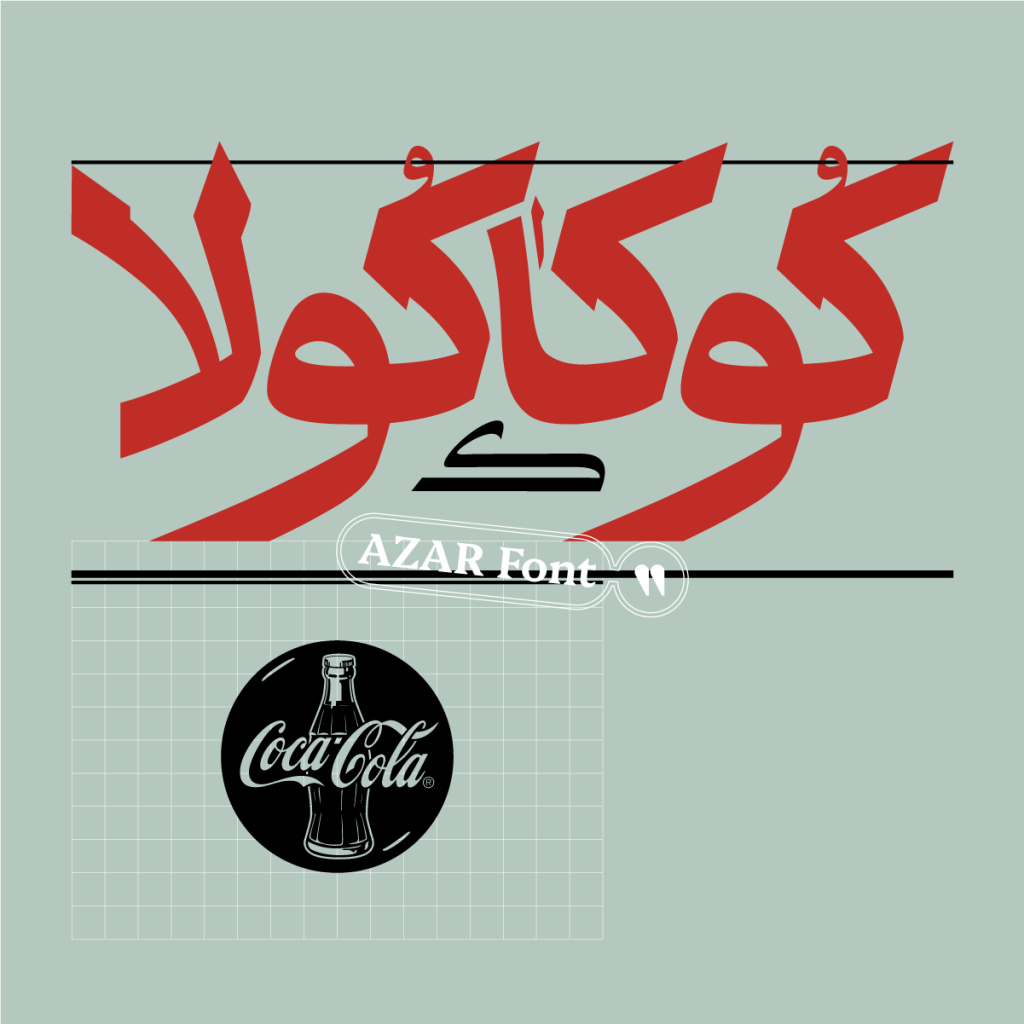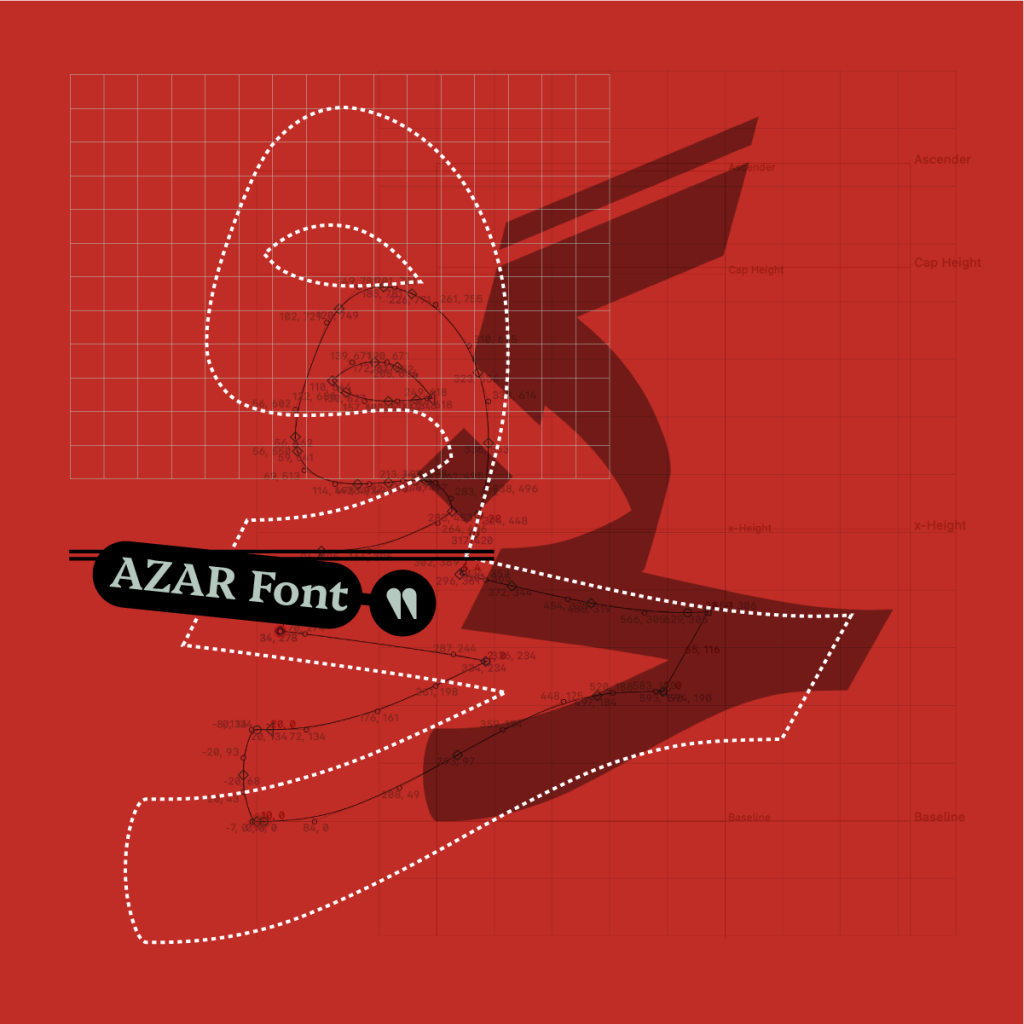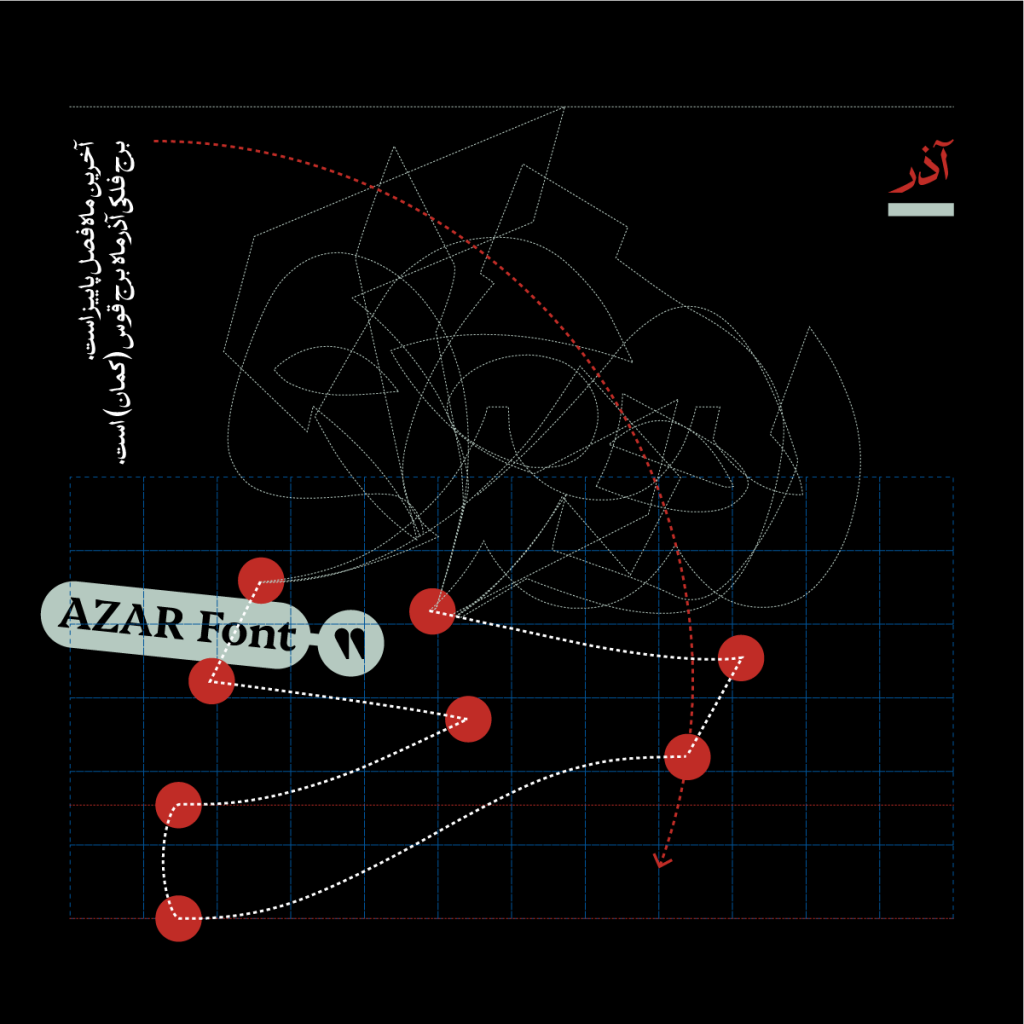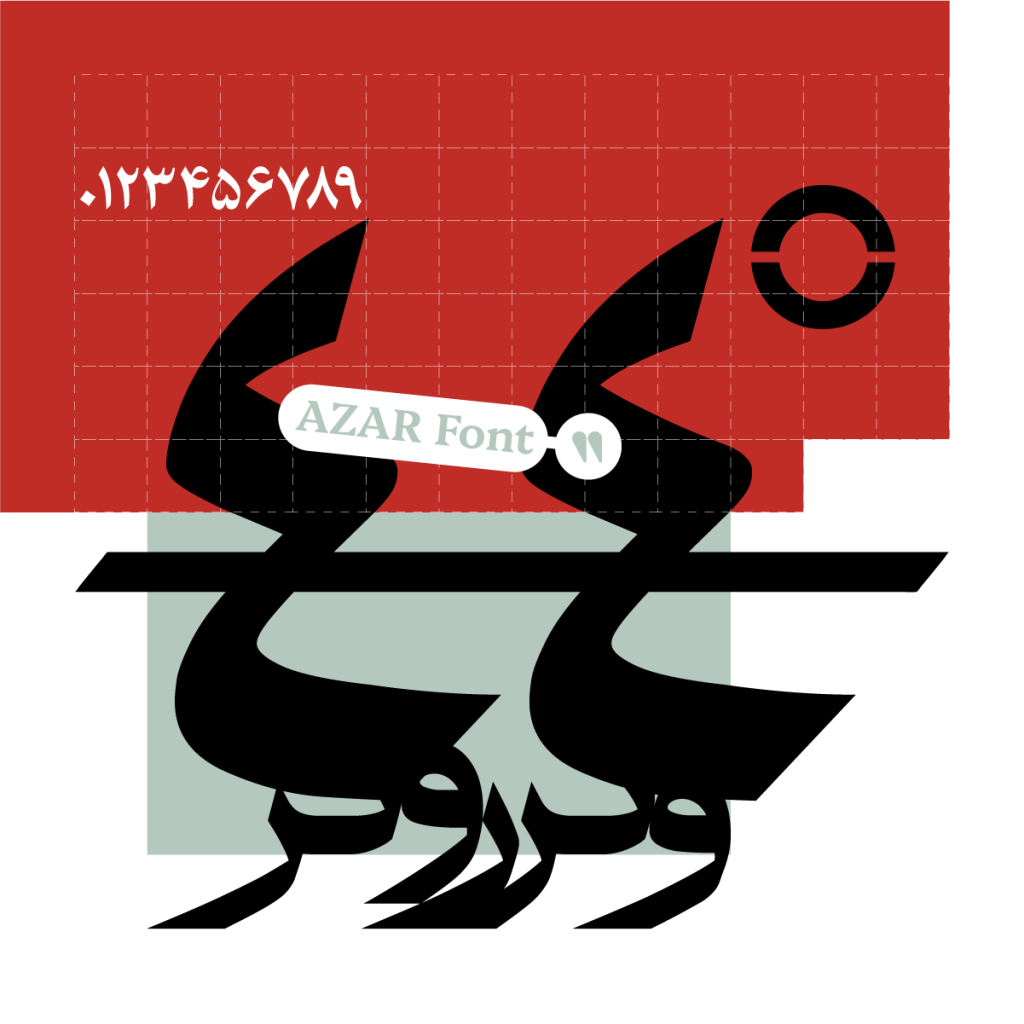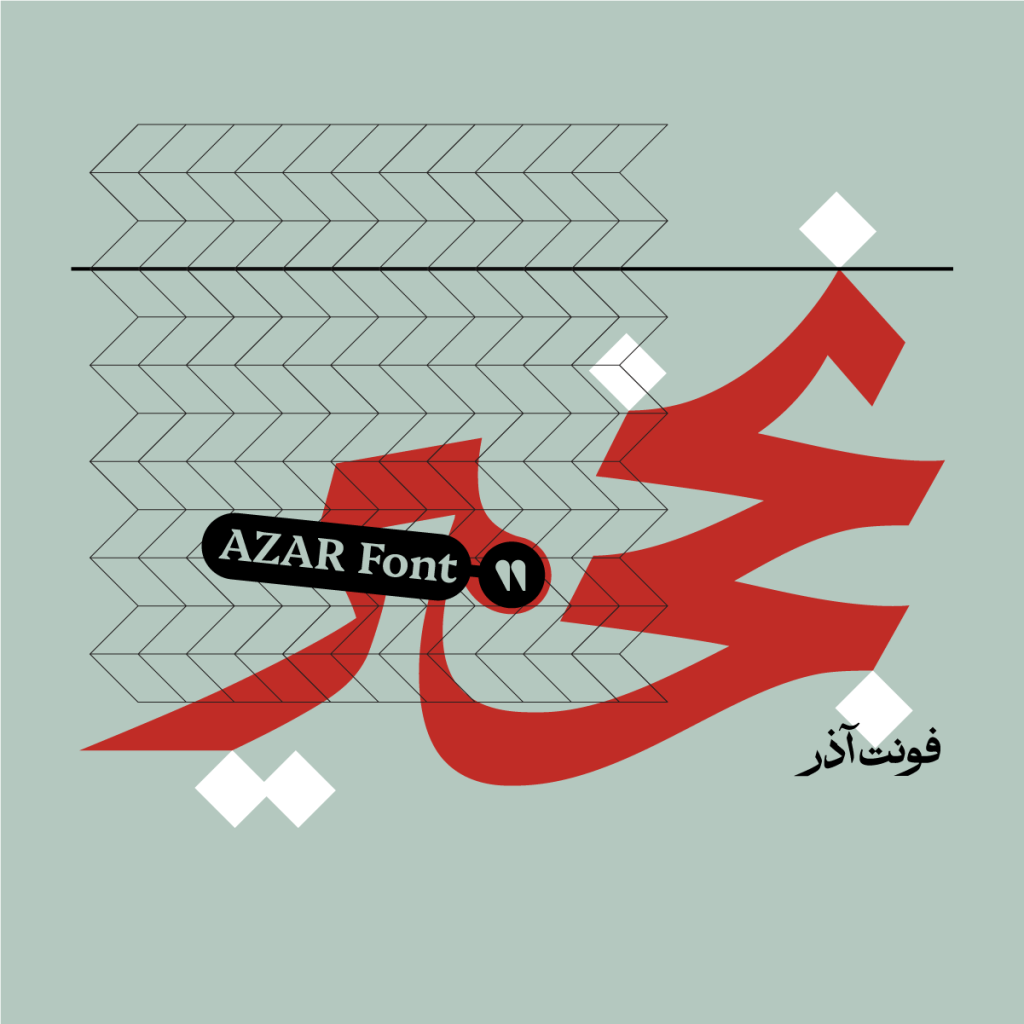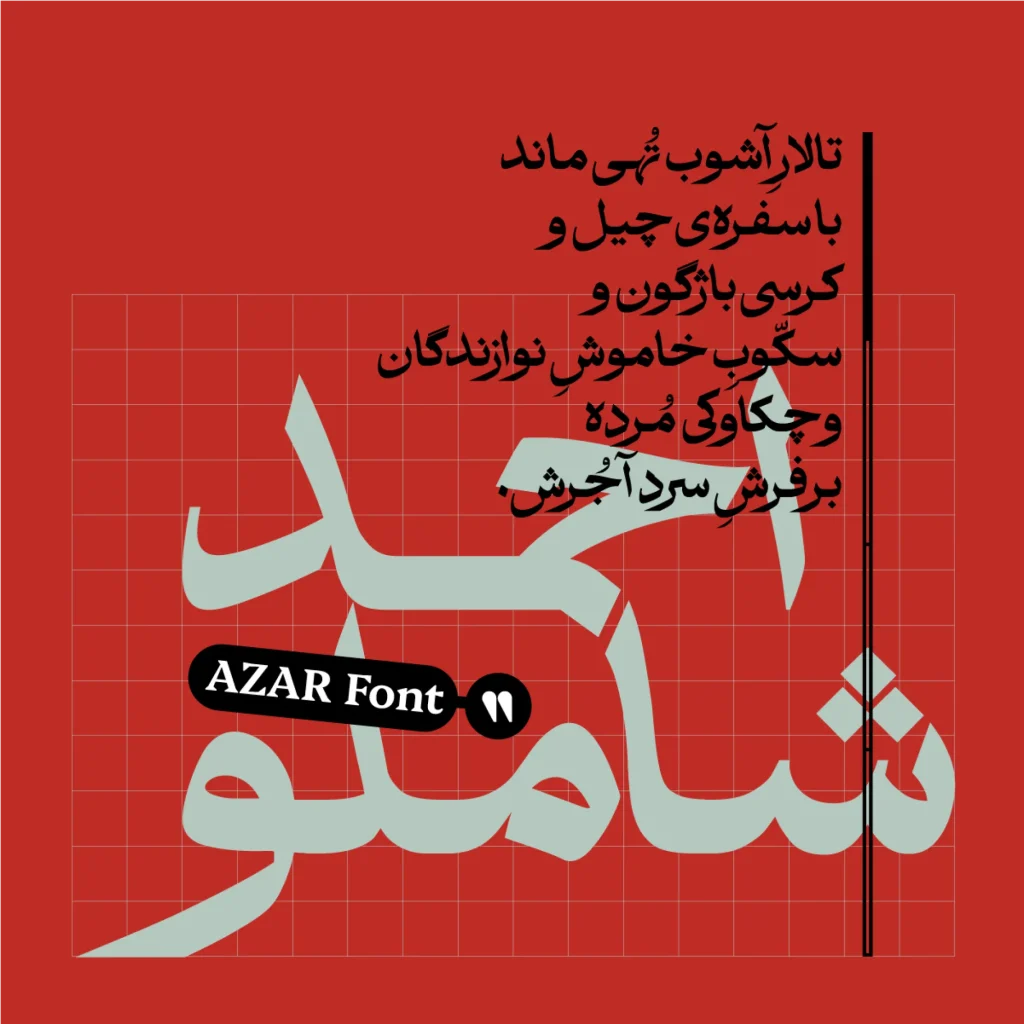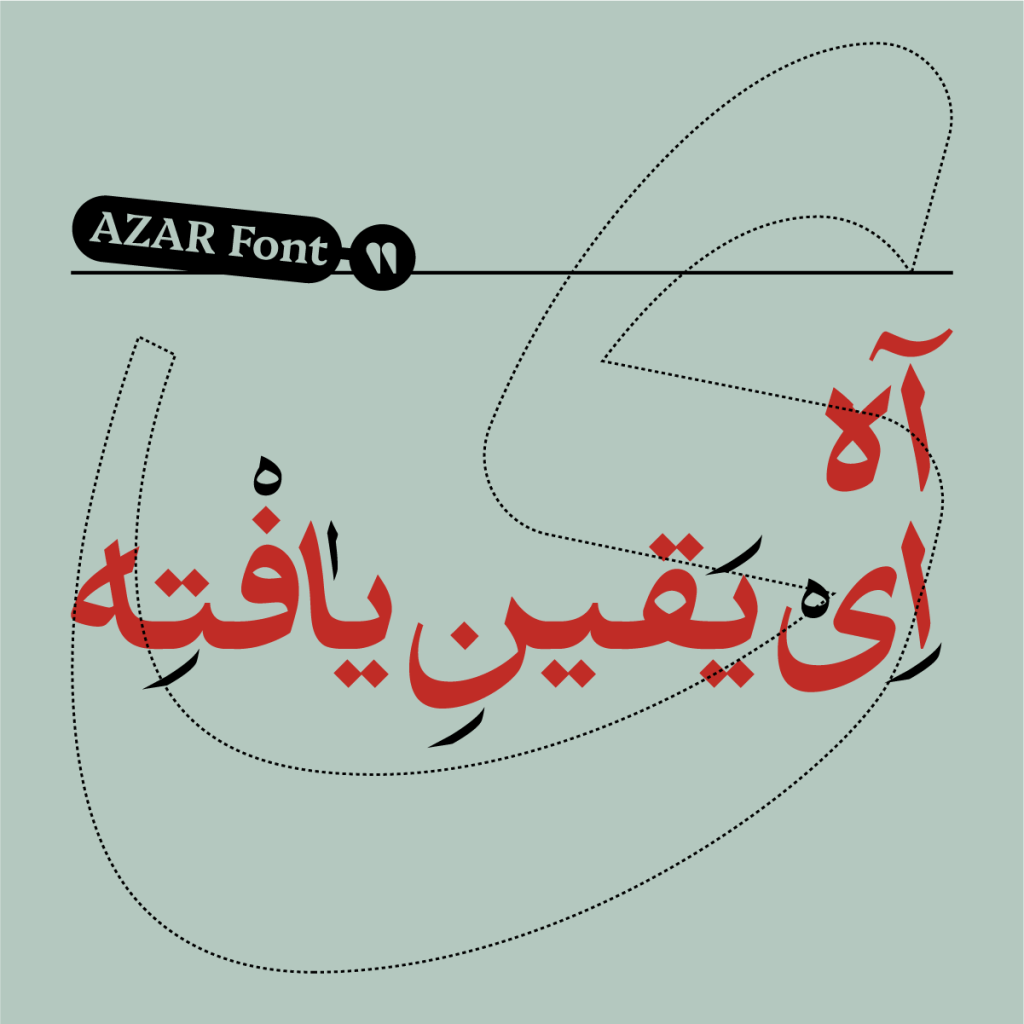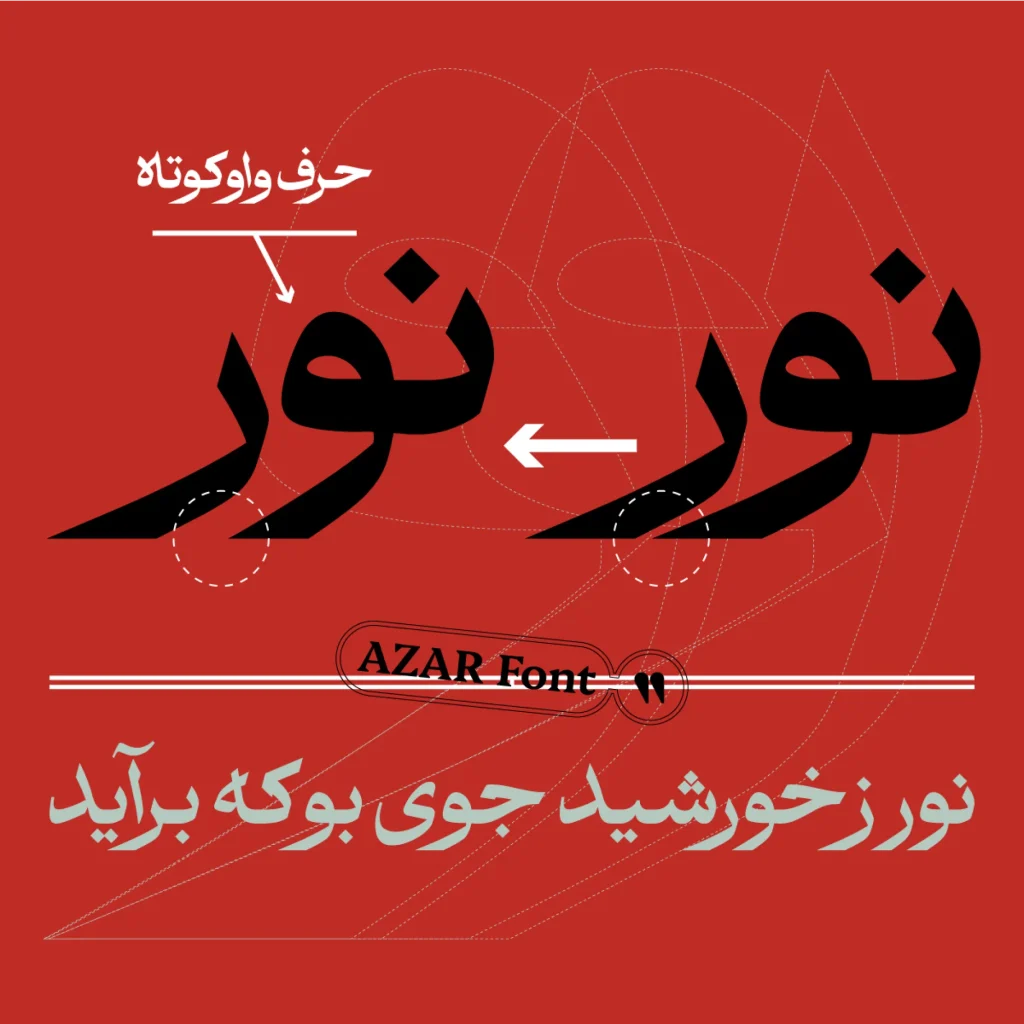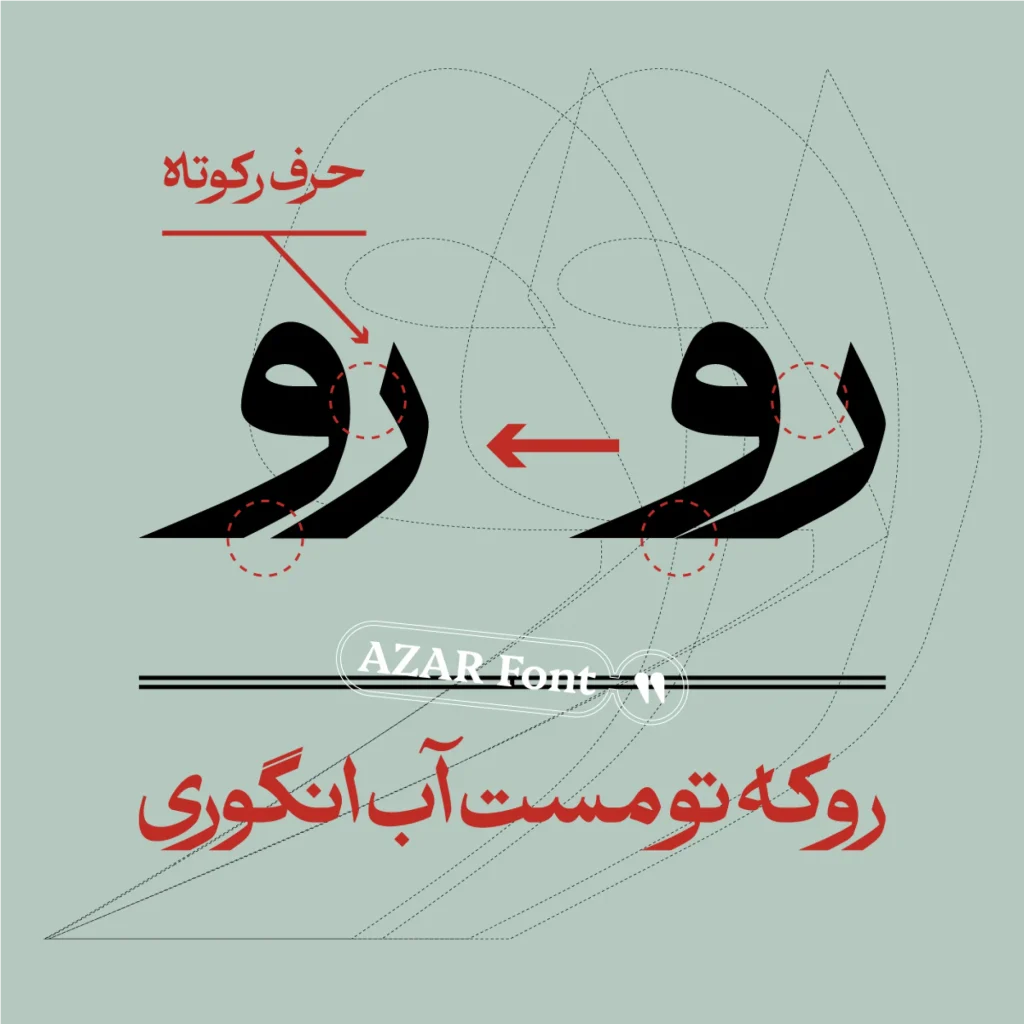
فونت اذر
فونت اذر قلمی از خانواده خط نسخ که فرم ها و حرکات خط ثلث را هم به ارث برده است. اکر به دنبال تایپ فیسی زیبا اصیل و هستید با ما همراه باشید تا قلم زیبای آذر را که ریشه های کهن قدیمی و کلاسیک دارد را به شما معرفی کنیم.
همخوانی و هماهنگی زیبا در تایپ فیس آذر
این تایپ فیس توسط طراحان متخصص تایپو گرافی فارسی متولد شده است . مهدی قاسمی رضا بختیاری فرد با با تمرکز بر ظرافت های طراحی و حفظ ساختارهای نوین آذز را به گونه ای خلق کرده اند که همخوانی و هماهنگی بی نظیر و منحصر به فردی در زیبایی شناسی و حفظ اصلت با مدل امروز و مدرن داشته باشد.
در مراحل ساخت قلم آذر همهٔ کاراکترها به نحوی ویرایش و بازسازی که در عین داشتن روحیه باستانی و حفظ ریشه های کلاسیک ساختار مدرن و منظم امروزی جهت کاربرد در فضای وب و دیجیتال نیز برقرار شود. با آذر می توان اصالت و تبارمندی و فضای کهن را به دنیای امروز دعوت نمود.
یکی از مهم ترین چالش ها در مسیر طراحی تایپ فیس آذر حفظ خوانایی همراه با تجربهی خواندن نوشتار با روحیهای تازه و دور از چهارچوبهای رایج طراحی بوده است. این قلم زیبا در ابتدای کار و نسخه های اولیه دارای یک وزن می باشد بدون شک آپدیت های آن را در آینده نزدیک در یافت خواهید نمود .
اگر بخواهیم قلمی نزدیک به این تایپ فیس را به شما عزیزان معرفی کنیم می توان به فونت دانگ اشاره کرد قلمی که از نقطه نظر هم خانوادگی بسیار شبیه به آذر است و شباهت نزدیک به آن دارد با این تفاوت که ساقه هایی بلند و نسبت فواصل خطوط کرسی آن بسیار زیاد است. این قلم مناسب برای متون کوتاه و عناوین و تیتر ها می باشد . در زیر می توانید تصاویر زیبای این قلم را مشاهد کنید.